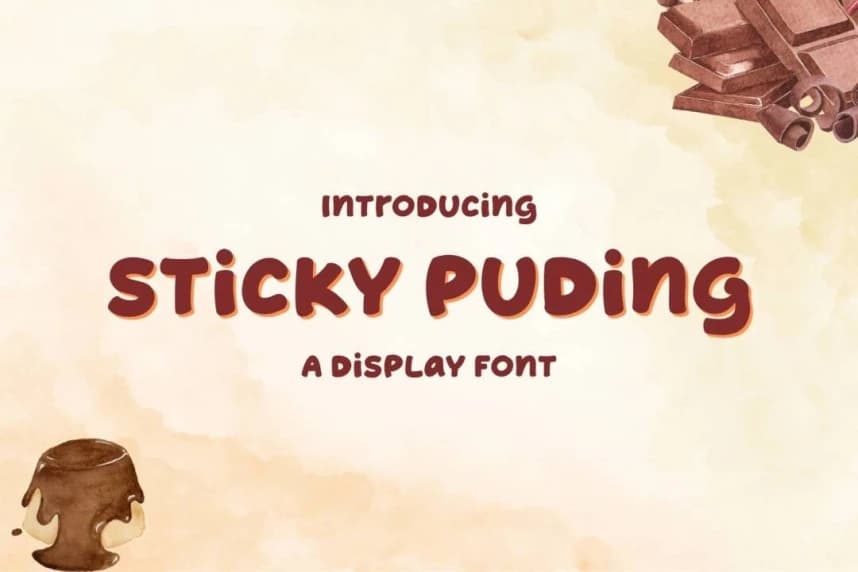
Sticky Puding Font, MJType tarafından tasarlanmış eğlenceli ve neşeli bir karikatür tarzı gösterim yazı tipidir. Kalın, yuvarlak harf biçimlerine sahip yumuşak ve puding benzeri bir görünüme sahiptir. Kalın hatları ve akıcı eğrileri, sevimli, arkadaşça ve hafif zıplayan bir his yaratır.
Sticky Puding Font, MJType tarafından tasarlanan eğlenceli ve oyuncu bir çizgi film tarzı gösterim fontudur; kalın, yuvarlak harf biçimlerine sahip, yumuşak ve «puding benzeri» bir görünüm sunar. Kalın şekilleri ve akıcı eğrileri sevimli, arkadaş canlısı ve hafifçe zıplayan bir his yaratır